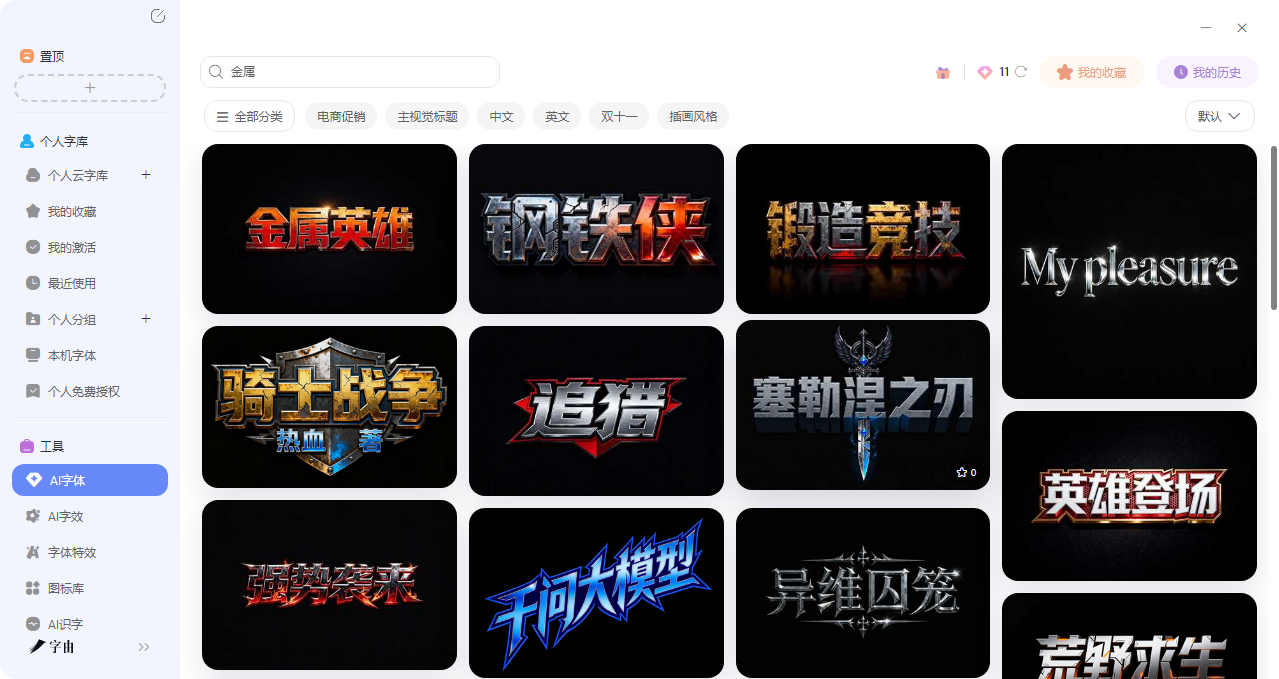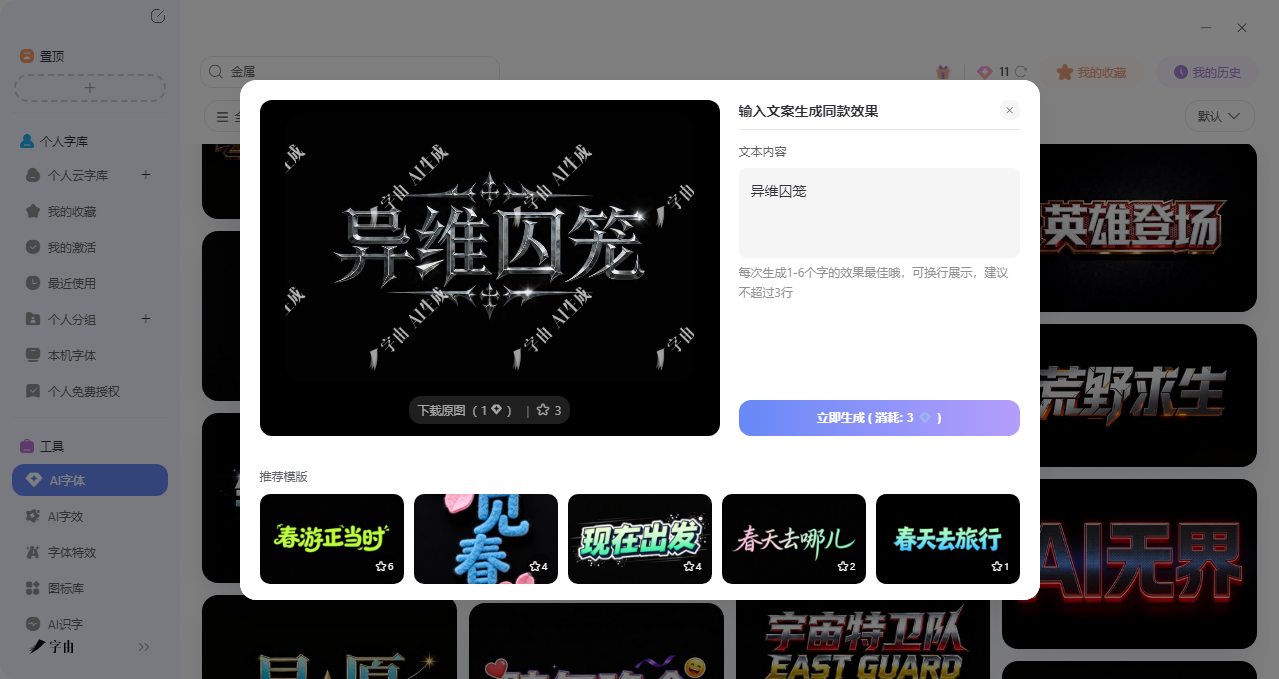
普通文字秒变金属质感,这5个网站太绝了
每当我们在设计当中看到有金属元素的时候第一反应都会是“有分量、有质感、冰冷坚硬”的感觉,这些元素往往会和重金属乐队巡演海报上冷硬的钢铁字、科技新品发布会背景上闪耀的铬金属Logo、甚至奶茶店招牌上复古做旧的铜板字相联系,这种带着重工业质感的高级字体,之前只能自己一点点手搓,或者用特定软件来渲染效果,对普通人来说上手难度太高。但是现在不一样了,金属质感字体制作网站能够快速地响应你的金属字体需求,那么我会在今天这篇文章中介绍5 个实用的金属质感字体制作网站,需要的可以收藏了!
第一个要推荐的金属质感字体制作工具是字由。字由可以直接让制作金属字体的门槛下降到最低,也就是说只要你会用字由里的工具,并且输入文字,你就可以制作,不需要你手动调图层、调质感等等步骤,那么下面我就会介绍免费制作的详细步骤:
第一步:打开字由客户端,左侧导航栏找到【工具】→【AI字体】,或者从首页【字体工具】→【AI工具】进入。这个功能内置了大量艺术字模板,从电商风到国潮风再到科技感,金属质感虽然没有被做到标签里,但是你可以直接搜索。
第二步:进入AI字体页面后,在搜索框里输入“金属”“钢铁”“铬金属”“铜质”“拉丝金属”等关键词,系统会自动筛选出所有带金属质感的模板。你也可以直接点进“科技“等分类里慢慢找。
第三步:选择喜欢的金属质感模板,搜索结果会展示各种金属风格的预览图,比如:
- 液态金属效果(像融化的金属流动感)
- 磨砂金属效果(哑光质感,低调高级)
第四步:输入文字。点击选中的模板,进入编辑页面。在输入框里填你想要生成金属效果的文字(比如“重金属之夜”“工业革命”“钢铁意志”)。
第五步:确认文案后,点“立即生成”,等20-30秒左右,系统就会输出设计好的金属质感艺术字图片。生成后可以预览效果,不满意就换其他模板再试。期间只是花费掉了每天免费送的算力点,不用花钱,完全免费。
后续下载到你的设计软件里可以进行再加工,甚至可以不用加工直接拿来用,这就是字由的方便之处。
除此之外,字由还有很多其他实用的字体,你可以选择去“免费字体”里寻找, 如果对以上的字体都不满意,只想拿到合适的字体以后进行自己加工,也是完全没有问题的,那么我会给大家介绍几款适合做金属质感字的普通字体:
- 字由源黑:厚实稳重,拉丝金属效果出来后很有分量感。
- 优设标题黑:方正有力,适合做铬金属高光标题。
- 字由文艺黑:粗重有力量,液态金属效果很有张力。
- 北窗墨刃:书法感强,做古铜做旧效果特别有味道。
2、Fontesh
Fontesh 是一个专门收集免费字体的平台,它的首页就有“Metal”分类,点进去能看到大量金属风格的字体。从截图看,这里展示的字体都非常有工业感:
- Dimosa Typeface:Display风格,免费商用
- Aporrheton Font:神秘感强的金属字
- Ghost Darko Font:暗黑风格,免费个人使用
- Darkness Font:暗黑金属感
- Pochwara Font:免费商用
- Sripnoxhz Font:免费商用
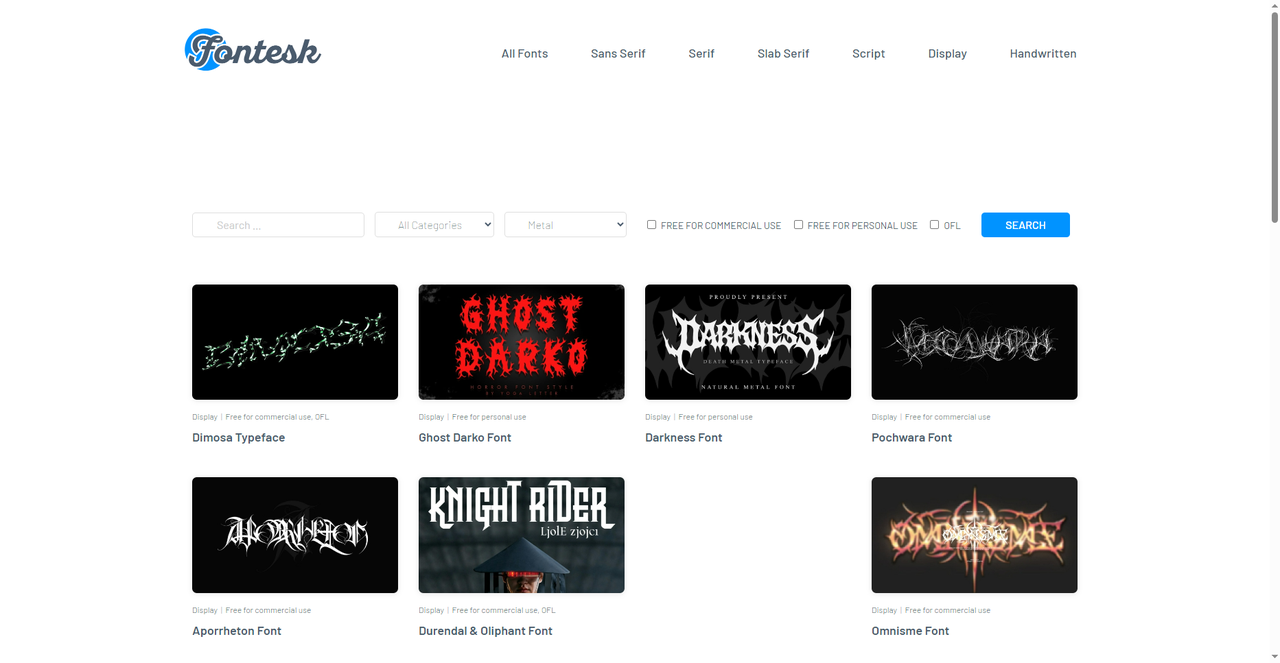
3、DAFONT
这个网站也是老熟人了,我经常会在作品中介绍它,除了往期介绍的一些字体类型,收录了一套非常经典的金属质感字体——Metallic 字体家族,由设计师Vladimir Nikolic 创作,而且包含了多种变体:
- MetallicLightSoft.ttf:轻柔金属感
- MetallicShadow.ttf:带阴影效果的金属字
当然,这些也都是免费个人使用,但是仅限个人使用!商用的话必须购买授权,作者也标注好了购买链接,十分便捷。这套字体特别适合做金属质感的标题、Logo、唱片封面等。每个变体都有不同的气质,可以组合使用,是十分经典的字体。
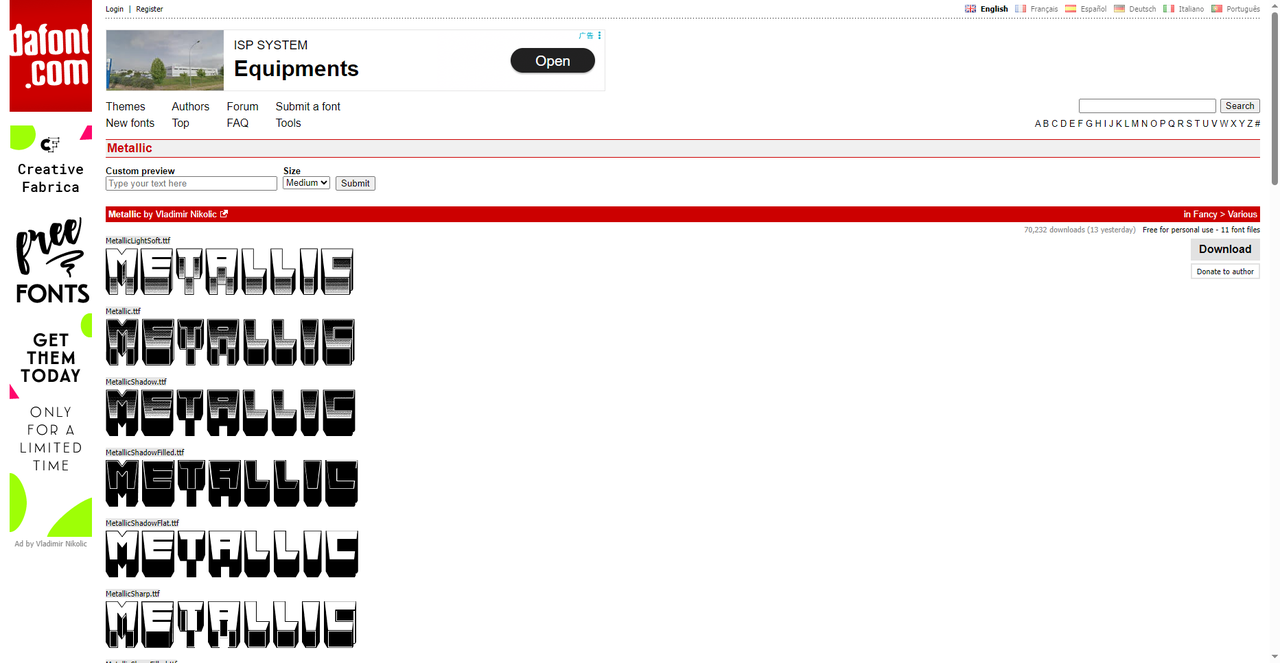
4、FreePik
Freepik 是全球知名的设计资源平台,搜索“metallic text effect”或“metal font”,能找到大量金属质感字体制作相关的矢量模板。里面的字体也是非常的高质丰富,部分素材可以免费下载使用(标注“free”),商用需查看具体授权。
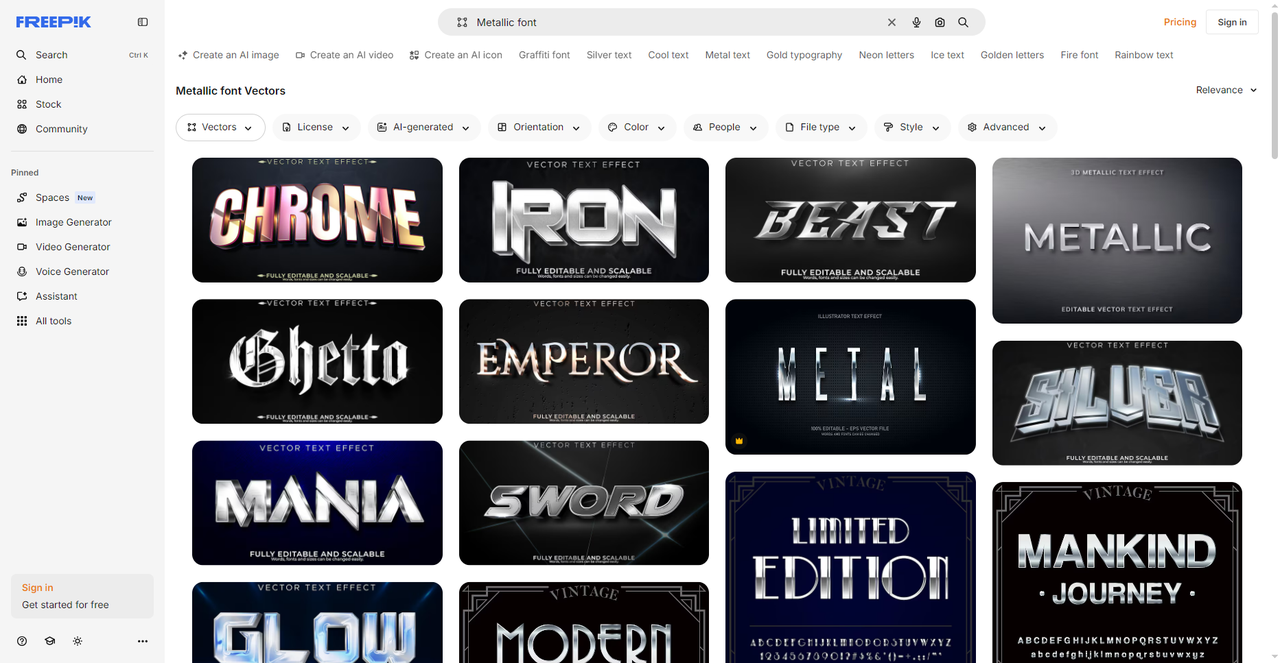
5、金属字生成器
从界面来看就可以知道这个工具十分简洁,功能包括:样式选择、图标与背景、动画支持和参数调节,这个工具特别适合需要精细调节金属效果的场景。比如你想要文字稍微弯曲成弧形,或者想调整每个字之间的间距,在这里都能轻松实现。